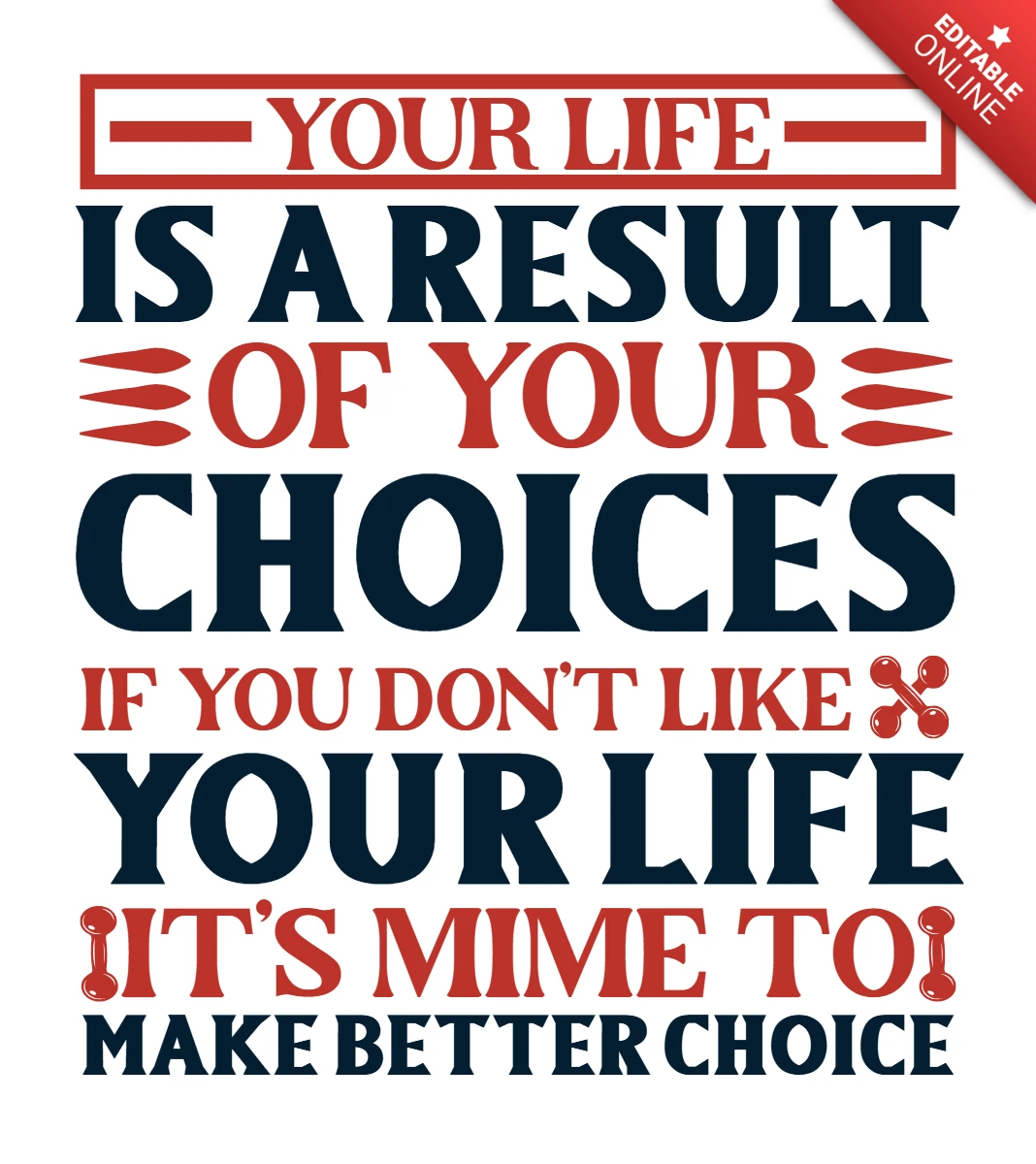
Motiverende typografie ontwerpsjabloon voor inspirerende levenskeuzes
Bewerken in Design Studio Downloaden in JPGVerhoog je fitnessmerk met onze inspirerende ontwerpsjablonen, met motiverende quotes en retro typografie die perfect zijn voor kleding, posters en stickers die kracht en levensstijlkeuzes belichamen.